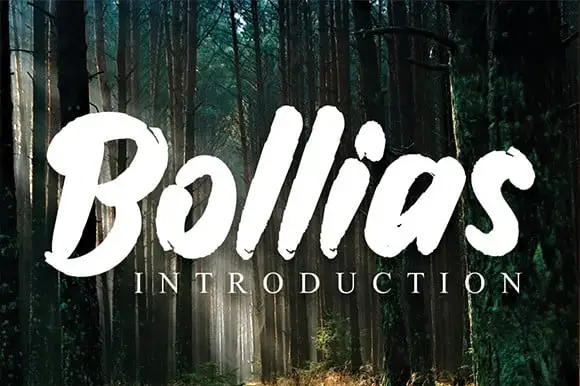
Bollias Brush Font
A Bollias Brush Font é perfeitamente adaptada para diversos projetos digitais e impressos no Brasil. Suas letras curvilíneas e elegantes são perfeitas para criar ambientes vibrantes em ambientes de wall displays, como a arquitetura moderna ou as decorações de eventos. Além disso, é uma escolha ideal para aplicativos digitais, especialmente quando se trata de personalizar publicações nas redes sociais, logos para anúncios e embalagens de produtos. Na área da design gráfico, a Bollias Brush Font oferece uma paleta de opções incrivelmente versátil. Seja para criar logotipos para eventos como festas de casamento ou para projetos que exigem um toque delicado em designs digitais de embalagem, a fonte é perfeita. Suas linhas e traços fluidos também fazem com que ela seja uma opção ótima para adicionar uma sensação personalizada às etiquetas dos produtos e até mesmo aos logotipos de suas próprias marcas em postagens de mídia social. Esta fonte é tão versátil quanto elegante, capaz de dar um toque sofisticado a qualquer projeto digital ou impresso. Com sua aparência arredondada e delicada, a Bollias Brush Font é uma opção inteligente para quem busca estilo e personalidade em seus materiais gráficos no Brasil.